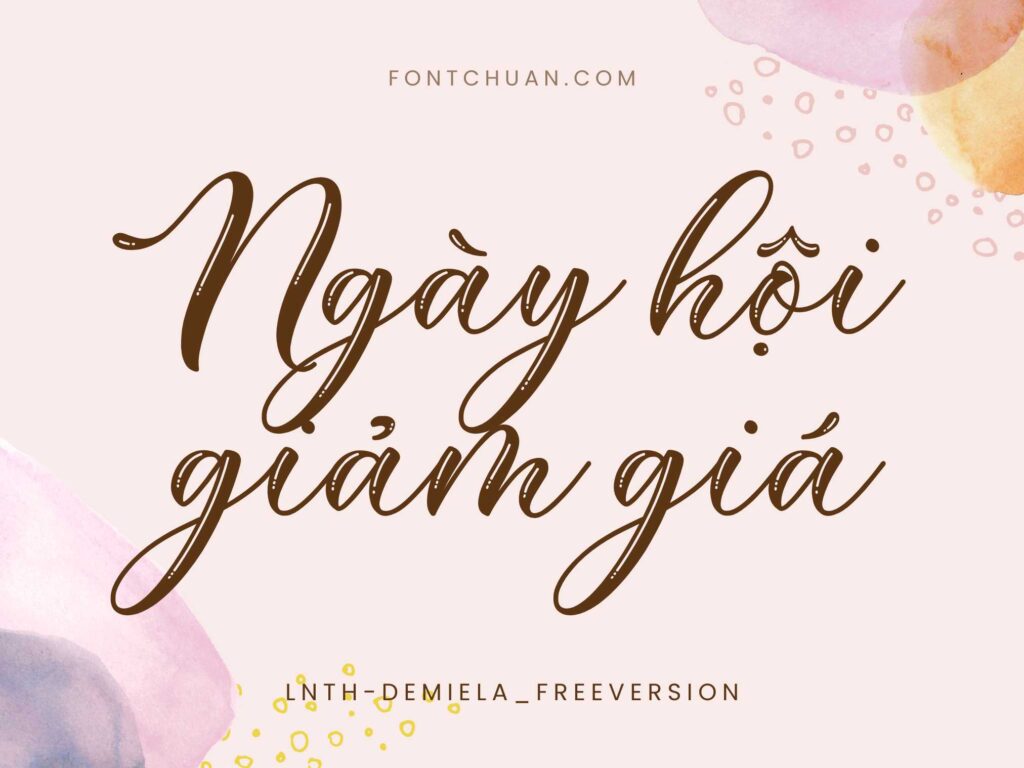
Font LNTH Demiela Việt Hóa
Tác giả Font: Jamalodin
Demiela là một phông chữ viết tay thanh lịch, mang phong cách hiện đại và mềm mại. Phông chữ này tạo cảm giác tinh tế và thân thiện, phù hợp cho nhiều dự án thiết kế cần sự nhẹ nhàng và nghệ thuật. Nhờ được Việt hóa bởi LNTH, Demiela hỗ trợ đầy đủ các ký tự tiếng Việt, giúp người dùng dễ dàng áp dụng trong các dự án đa ngôn ngữ. Phông chữ này đã được sưu tầm và đăng tải bởi thành viên của Font Chuẩn, đáp ứng nhu cầu đa dạng của cộng đồng thiết kế.
Về đặc điểm thiết kế, Demiela sở hữu các ký tự được vẽ tỉ mỉ với những đường nét mượt mà, mang lại cảm giác tự nhiên và thanh thoát. Phông chữ này đặc biệt phù hợp để sử dụng như Font chữ ký, cũng như cho các dự án như thiệp mời, bìa sách, poster, logo và các ấn phẩm quảng cáo, giúp truyền tải sự tinh tế và nghệ thuật. Ngoài ra, Demiela cũng thích hợp cho các sự kiện như lễ hội, sinh nhật, Valentine và Trung thu, tạo nên không gian ấm áp và lãng mạn. Trong lĩnh vực ngành nghề, phông chữ này được ứng dụng rộng rãi trong quảng cáo, thiết kế thiệp cưới, giáo dục và công nghệ, góp phần tạo điểm nhấn độc đáo và chuyên nghiệp cho các sản phẩm và thương hiệu.